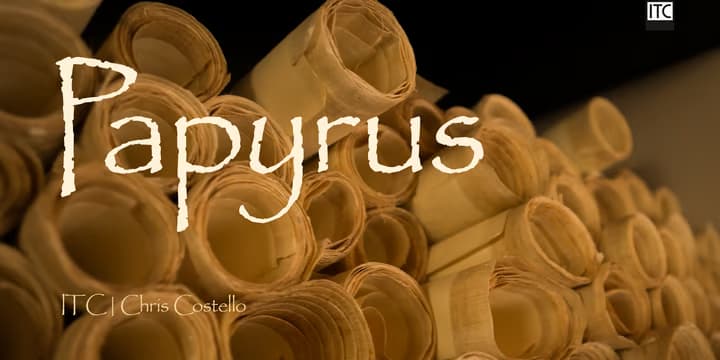
Papyrus
なんか不意にこの書体を見かけたので紹介。ラフなカリグラフィーヒューマニスト。15世紀頃に現れたヒューマニスト体を元にデザインされた書体で、往時のものよりはかなり細めのウェイトで、グリフも結構ラフでカジュアルになっている。エッジもガタガタでラフな紙に書いたような雰囲気があり、「パピルス」の名にふさわしい。ちなみにこの書体は以前は Mac に標準搭載され、またかなり多用されたために「もういいよクソダセェ」と欧米のデザイナーからは Comic Sans と同じぐらい嫌われていた(笑)。とはいえ、映画「アバター」のタイトルロゴの元になっていたり、徐々に復権の兆しはあるかと思う。筆者は結構好きな書体。1ウェイト。